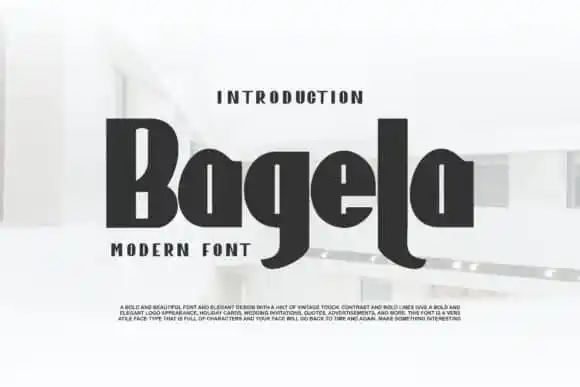
Bagela Sans Serif Font – Download Grátis
Introduzimos Bagela Sans Serif Font, uma tipografia geométrica perfeita que atração visualmente para quem a olha. Heisman é totalmente calibado e usa-se facilmente. Foi cuidadosamente criada pelo designer de fontes chamado Vunira. Bagela é um tipo sério e moderno, ideal tanto para enquadramentos no entorno de trabalho quanto para estilos mais leves. Seu charme casual faz com que pareça natural e fácil de ler, tudo ao mesmo tempo. Essa fonte se destaca em qualquer contexto, seja ela usada em fundos movimentados ou como título isolado. Com sua elegância perfeita, Bagela Sans Serif Font será uma escolha ótima para projetar logotipos, criar materiais de marketing e decorar websites. Afinal, Bagela Sans Serif é um ícone da tipografia moderna que certamente se destaca na sua próxima projeto visual.